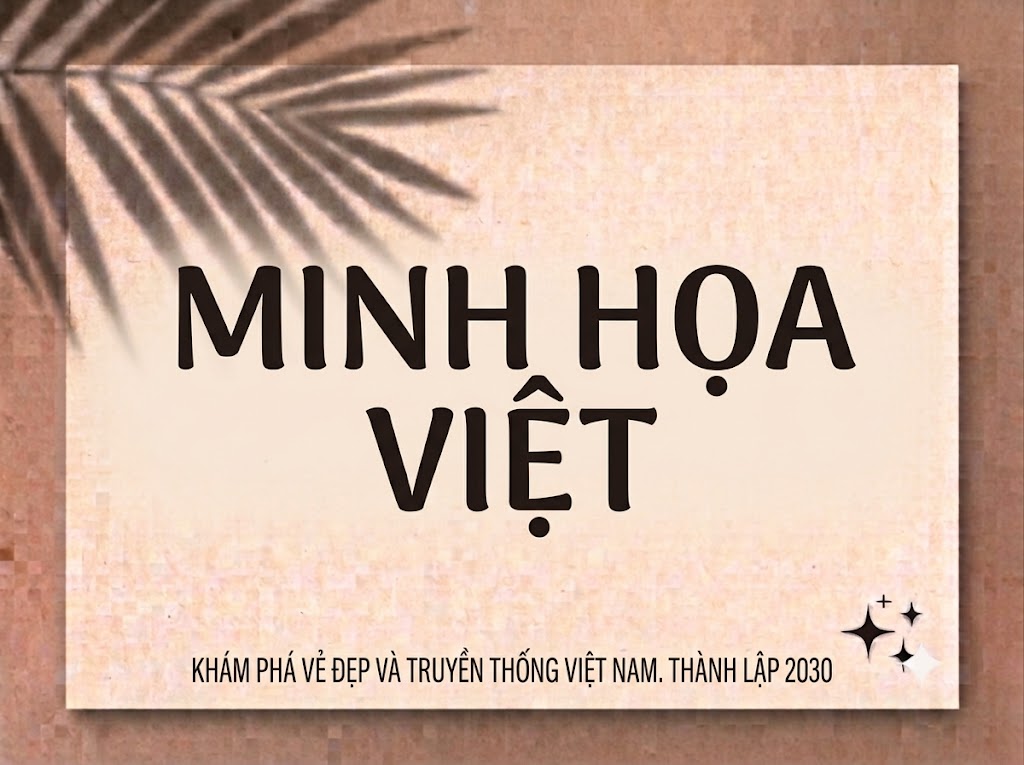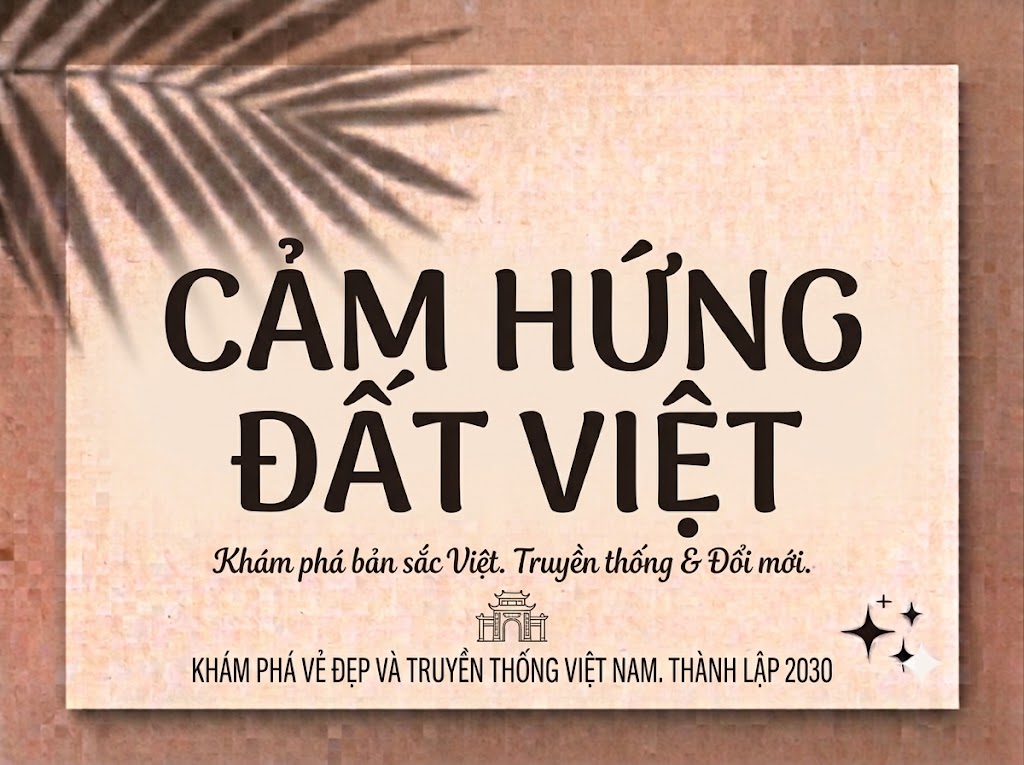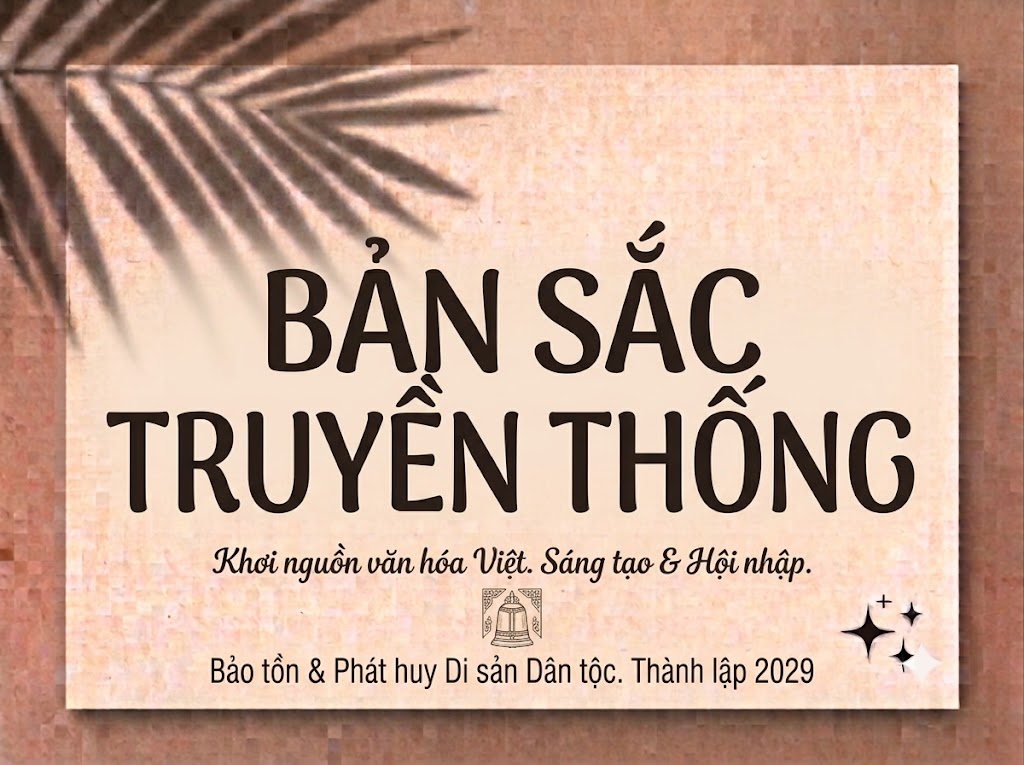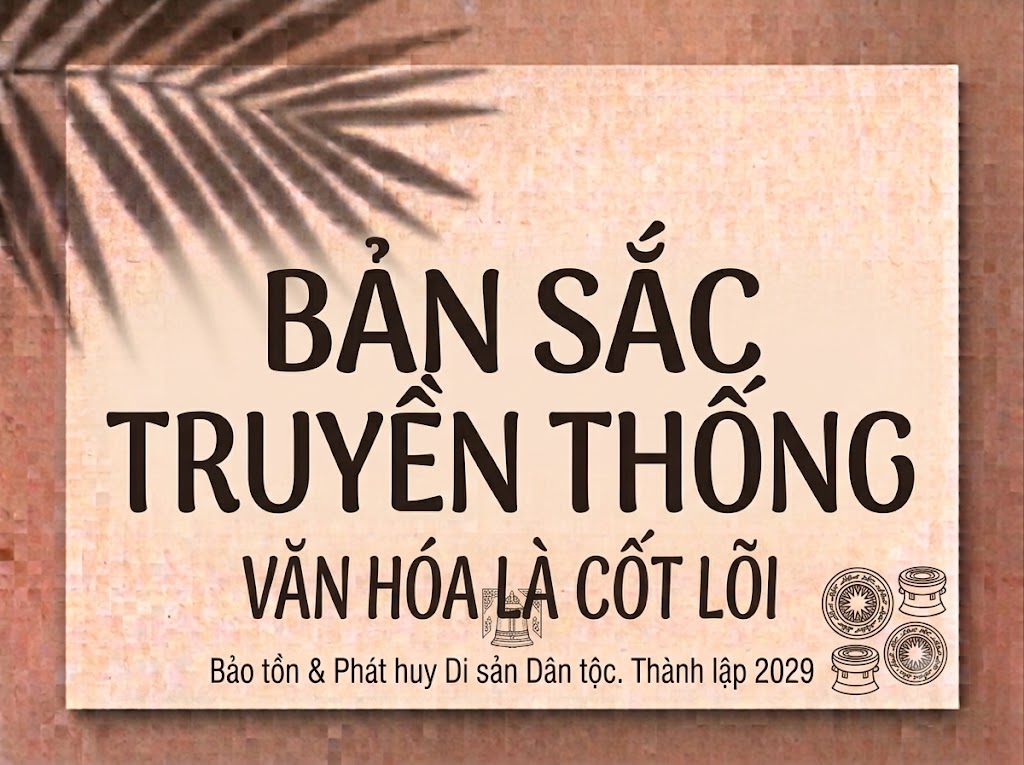
1FTV Pixabler
Trong bối cảnh tiếp cận thông tin nhanh trên các nền tảng mạng xã hội, một phông chữ không chân (sans-serif) gọn gàng, có độ dày lý tưởng và dễ đọc luôn là lựa chọn ưu tiên hàng đầu. Nó quyết định việc người xem có dừng lại vài giây để đọc hết thông điệp của bạn trên bảng tin hay không.
Nếu bạn đang tìm kiếm một bộ chữ hiện đại, sở hữu các đường bo góc mềm mại mang hơi hướng kỹ thuật số nhưng vẫn giữ được sự chuyên nghiệp, sạch sẽ thì font 1FTV Pixabler chính là mảnh ghép hoàn hảo cho hộp công cụ sáng tạo của bạn.
Giới thiệu về font 1FTV Pixabler
Font 1FTV Pixabler là một phông chữ hiển thị không chân được thiết kế với cấu trúc hình khối cân đối, vững chãi và mang tính ứng dụng thực tế rất cao trong môi trường đồ họa số.
Đặc điểm nổi bật của phong cách thiết kế Pixabler
Sức hút lớn nhất của font 1FTV Pixabler đến từ sự kết hợp hài hòa giữa cấu trúc geometric hình học đứng dáng và các góc bo tròn mềm mại nhẹ nhàng:
Thân thiện và trực diện: Các nét chữ được bo cạnh tinh tế giúp giảm bớt sự thô cứng của các dòng font khối, mang lại cảm giác trẻ trung, hiện đại và rất dễ tiếp cận.
Tỷ lệ chữ vàng: Khoảng trống bên trong ký tự (counter) cùng độ dày nét chữ được tính toán tỉ mỉ, giúp các khối chữ khi đứng cạnh nhau tạo nên một kết cấu chữ vô cùng vững chãi, thoáng đãng.
Hỗ trợ hệ ký tự hoa – thường đồng bộ: Pixabler tích hợp trọn vẹn cả hệ thống chữ cái viết thường bên cạnh bộ chữ viết hoa cơ bản, mang lại sự linh hoạt tối đa khi bạn cần sắp xếp bố cục phân cấp nội dung chính – phụ trên cùng một ấn phẩm quảng cáo.
Hệ thống khoảng cách chữ (kerning) và độ giãn dòng đã được căn chỉnh chuẩn xác, giúp các từ khi đi liền nhau đạt được sự mạch lạc tuyệt đối, không bị dính nét hay gây ngột ngạt khi đọc nhanh.
Tích hợp đầy đủ bộ chữ cái hoa – thường, dãy chữ số từ 0-9 phom dáng hiện đại cùng hệ thống các ký tự đặc biệt, dấu câu thông dụng (
Bản Việt hóa chuẩn chỉnh từ đội ngũ 1FTV giúp bạn hoàn toàn yên tâm gõ các văn bản tiếng Việt có dấu phức tạp mà không lo gặp phải tình trạng lỗi hiển thị dấu câu hay nhảy font lỗi thời.
Hình ảnh demo thực tế của font 1FTV Pixabler
Để dễ dàng đánh giá khả năng hiển thị trực quan và co giãn linh hoạt của phông chữ này trên các tỷ lệ kích thước khác nhau:
Kích thước nhỏ (12pt – 24pt): Nhờ cấu trúc không chân thông thoáng, bộ chữ thường và dãy số vẫn hiển thị vô cùng ngay ngắn, sắc nét và cực kỳ dễ đọc ngay cả trên màn hình điện thoại di động cỡ nhỏ.
Kích thước lớn (36pt – 72pt): Đây là đất diễn lý tưởng nhất để font phô diễn toàn bộ sự hiện đại, tinh tế của các đường bo góc, tạo tác động thị giác mạnh mẽ chiếm trọn sự chú ý cho các dòng headline chính.
Ứng dụng của font Pixabler trong thiết kế đồ họa và làm video
Sở hữu nét cá tính hiện đại, sạch sẽ và cấu trúc hoa – thường linh hoạt, font 1FTV Pixabler mở ra không gian sáng tạo vô cùng rộng lớn cho các dự án truyền thông và marketing thế hệ mới:
Làm tiêu đề và phụ đề cho video ngắn (TikTok, Reels, Shorts): Dáng chữ đứng ngay ngắn, rõ nét cực kỳ hoàn hảo cho các khung hình dọc tỷ lệ 9:16. Độ rõ ràng của nét chữ giúp lời thoại phụ đề hoặc dòng giật tít hiển thị một cách tự nhiên, cuốn hút người xem lướt feed dừng lại ngay lập tức mà không che khuất các chủ thể chính của video.
Thiết kế ảnh thu nhỏ mạng xã hội (Thumbnail): Vũ khí tuyệt vời để tạo nên những chiếc thumbnail YouTube, TikTok quảng cáo sản phẩm, nội dung công nghệ, e-commerce hoặc chia sẻ kiến thức nhằm bứt phá tỷ lệ nhấp chuột (CTR) nhờ độ hiển thị trực diện từ khoảng cách xa.
Banner quảng cáo sản phẩm và E-commerce: Hoàn hảo cho các poster giới thiệu sản phẩm thời trang, mỹ phẩm, đồ gia dụng thông minh hoặc thiết bị công nghệ cần sự tinh tế, ngăn nắp và hiện đại.
Nhận diện thương hiệu phong cách tối giản: Phù hợp làm logo dạng chữ khối, biểu ngữ quảng cáo hoặc thiết kế nhãn mác, bao bì cho các local brand, tiệm cà phê hoặc các studio sáng tạo hướng tới tệp khách hàng trẻ tuổi.